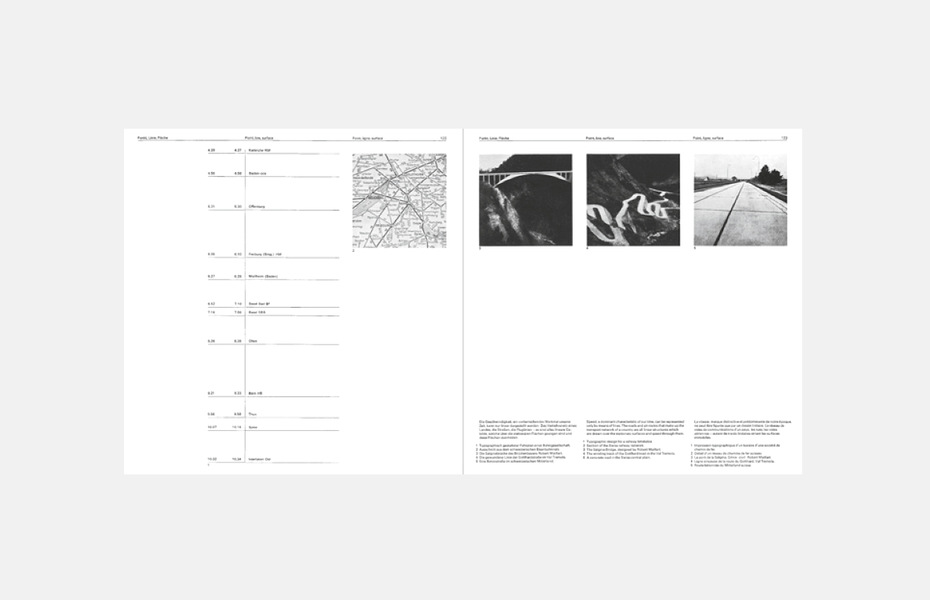
danke Emil Ruder
От ре­дак­ции Ров­но пять­де­сят лет на­зад в из­да­тель­стве Ар­ту­ра Ниг­гли (го­род Ни­дертёй­фен, Швей­ца­рия) вы­шла кни­га Эми­ля Ру­де­ра (1914–1970) «Ти­по­гра­фи­ка». В то вре­мя гра­фи­че­ский ди­зайн в Ев­ро­пе ис­пы­ты­вал не­обык­но­вен­ный подъ­ём, ко­то­рый во мно­гом был свя­зан с де­я­тель­но­стью учеб­ных цен­тров в Ба­зе­ле, Цю­ри­хе и Уль­ме. Пе­ре­до­вая шко­ла ди­зай­на, по­явив­ша­я­ся в не­драх Ба­у­ха­у­за, воз­ро­жда­лась в но­вом, по­сле­во­ен­ном кон­тек­сте. Вме­сте с про­мыш­лен­ным ди­зай­ном и ар­хи­тек­ту­рой но­вую жизнь по­лу­чи­ла и ти­по­гра­фи­ка на пра­вах уни­каль­ной дис­ци­пли­ны со сво­и­ми пе­да­го­ги­че­ски­ми ме­то­ди­ка­ми. Уси­ли­я­ми Эми­ля Ру­де­ра, Ад­ри­а­на Фру­ти­ге­ра, Мак­са Бил­ла, Ар­ми­на Хоф­ма­на и дру­гих ди­зай­не­ров она об­ре­ла то, что не мог дать ти­по­гра­фи­ке аван­гард 20-х: фун­да­мент, осно­ва­тель­ность, кон­цеп­ту­а­лизм. Квад­рат­ный том Ру­де­ра, из­дан­ный на трёх язы­ках (не­мец­ком, ан­глий­ском и фран­цуз­ском), пред­став­ля­ет со­бой уни­каль­ный кон­спект лек­ций, ко­то­рые ти­по­граф чи­тал в те­че­ние 20 лет в Ба­зель­ской выс­шей шко­ле ремё­сел. Труд Ру­де­ра бы­стро рас­про­стра­нил­ся в Ев­ро­пе и Аме­ри­ке и вы­дер­жал ряд пе­ре­из­да­ний как в Швей­ца­рии, так и в дру­гих стра­нах.
Вы­пу­щен­ный Дмит­ри­ем Аро­но­вым осе­нью ре­принт со­вет­ско­го из­да­ния «Ти­по­гра­фи­ки» (М.: Кни­га, 1982; пе­ре­вод с не­мец­ко­го, по­сле­сло­вие и ком­мен­та­рий Мак­си­ма Жу­ко­ва) — но­вый ру­беж в ис­то­рии этой кни­ги. За­но­во свёр­стан­ная и на­бран­ная из­да­те­лем, она при­бли­же­на ком­по­зи­ци­он­но и по­ли­гра­фи­че­ски к швей­цар­ско­му пер­во­из­да­нию. Не­смот­ря на то что в рус­ском из­да­нии нет па­рал­лель­ных тек­стов на дру­гих язы­ках (и, со­от­вет­ствен­но, трёх­ко­лон­ни­ка), в его осно­ве ле­жит мо­дуль­ная сет­ка Ру­де­ра, ко­то­рую не уда­лось в точ­но­сти со­хра­нить из-за по­греш­но­стей по­ли­гра­фии в 1982 го­ду в Моск­ве. В ны­неш­нем ре­прин­те и фор­мат, и вы­бор ма­те­ри­а­лов, и пе­чать не на­ру­ша­ют струк­ту­ру по­лей и про­пор­ции, из­бран­ные Ру­де­ром для сво­ей кни­ги.
По­че­му это важ­но — про­из­не­се­но в вы­ступ­ле­нии од­но­го из са­мых та­лантли­вых ти­по­гра­фов со­вре­мен­но­сти Гель­му­та Шми­да об Эми­ле Ру­де­ре в свя­зи со сто­ле­ти­ем со дня ро­жде­ния по­след­не­го. Один из вер­ных уче­ни­ков Ру­де­ра, Шмид рас­ска­зы­ва­ет об ис­то­рии воз­ро­жде­ния этой кни­ги в 2001 го­ду в из­да­тель­стве Niggli по­сле че­ре­ды гру­бых и пи­рат­ских пе­ре­из­да­ний «Ти­по­гра­фи­ки». В транс­крип­те ре­чи ска­за­но, ра­зу­ме­ет­ся, не толь­ко об этом. Бла­го­да­ря Шми­ду мы мо­жем по­гру­зить­ся в ат­мо­сфе­ру кур­са ти­по­гра­фи­ки в Выс­шей шко­ле ремё­сел в Ба­зе­ле. Имен­но ра­бо­ты уче­ни­ков Ру­де­ра тех лет со­ста­ви­ли осно­ву «Ти­по­гра­фи­ки» — кни­ги не про то, как де­лать, не про кро­хо­бор­ство в на­бо­ре и су­е­ту пра­вил и ис­клю­че­ний, а про мыш­ле­ние, шко­лу, уме­ние вы­стра­и­вать струк­ту­ру и мыс­лить ти­по­гра­фи­че­ски.
danke Emil Ruder
Речь об Эми­ле Ру­де­ре к 100-ле­тию
со дня ро­жде­ния. То­кио, 2014
Най­ти и со­хра­нить твор­че­ский сти­мул в ис­ход­ной за­да­че — са­мое важ­ное для Ру­де­ра. Его ме­тод обрёл вне­вре­мен­ное ка­че­ство, вот по­че­му он так зна­чим и при­вле­ка­те­лен се­го­дня...
Я сра­зу по­нял, что нуж­но смот­реть по сто­ро­нам: в Швей­ца­рии ти­по­гра­фи­ка од­на, в Ба­зе­ле — дру­гая, а ти­по­гра­фи­ка Эми­ля Ру­де­ра не ­по­хо­жа ни на од­ну из них. «Да­же не по­ка­зы­вай, я знаю, что они там де­ла­ют», — ска­зал Ру­дер, ко­гда я по­пы­тал­ся про­де­мон­стри­ро­вать ему свои ра­бо­ты. «Там» — это в За­пад­ной Гер­ма­нии, на гра­ни­це со швей­цар­ским Ба­зе­лем. Так слу­чи­лось, что я жил по ту сто­ро­ну гра­ни­цы, в го­ро­де Вайль-ам-Райн. Путь до Ба­зе­ля был лёг­кой про­гул­кой к гра­ни­це. Путь к ти­по­гра­фи­ке ле­жал че­рез гра­ни­цу. В ап­ре­ле 1960 го­да я по­лу­чил раз­ре­ше­ние на пе­ре­се­че­ние по­гра­нич­ной зо­ны, что­бы стать бли­же к ти­по­гра­фи­ке.
Мо­им пер­вым ти­по­граф­ским опы­том под ру­ко­вод­ством Эми­ля Ру­де­ра бы­ли два­дцать ва­ри­ан­тов не­боль­шой га­зет­ной ре­кла­мы. Во­семь из них вы­ста­ви­ли в но­я­бре 1961 го­да в Graphisches abc, не­мец­ком жур­на­ле для на­чи­на­ю­щих гра­фи­че­ских ди­зай­не­ров. Во вве­де­нии бы­ло на­пи­са­но: «Юный уче­ник с юго-вос­то­ка фе­де­ра­тив­ной рес­пуб­ли­ки и се­рия ре­клам­ных ма­те­ри­а­лов, из­го­тов­лен­ных им под ру­ко­вод­ством гос­по­ди­на Эми­ля Ру­де­ра». Жур­нал ис­поль­зо­вал мой ва­ри­ант об­лож­ки, ко­то­рый я со­здал под яв­ным вли­я­ни­ем Ру­де­ра и от­пра­вил под его же име­нем. «Нам за­пла­тят?» — мо­мен­таль­но от­ре­а­ги­ро­вал Ру­дер, ко­гда я по­ка­зал ему этот но­мер жур­на­ла.
Курс ти­по­гра­фи­ки в Выс­шей шко­ле ремё­сел в Ба­зе­ле
В 1950-х и 60-х го­дах Ба­зель стал цен­тром при­тя­же­ния для мо­ло­дых ти­по­гра­фов и ди­зай­не­ров из раз­ных стран во мно­гом бла­го­да­ря Ру­де­ру и его ра­бо­там. Он учил ди­зай­не­ров мыс­лить ши­ро­ко, вос­пи­ты­вал на­бор­щи­ков и пе­чат­ни­ков, зна­ко­мил гра­фи­че­ских ди­зай­не­ров с ти­по­гра­фи­ей, вёл курс по вы­со­кой пе­ча­ти, да­вал ве­чер­ние уро­ки под эги­дой ба­зель­ско­го Со­ю­за ти­по­гра­фов (Handsetzer-Vereinigung Basel). Кро­ме то­го, Ру­дер раз­ра­бо­тал про­грам­му го­до­во­го кур­са ти­по­гра­фи­ки, на ко­то­рый еже­год­но при­ни­мал двух-трёх сту­ден­тов.
«Дорога в Базель» — опуб­ли­ко­ван­ный в 1997 го­ду из­да­тель­ством Robundo в То­кио сбор­ник очер­ков о ти­по­гра­фи­ке, на­пи­сан­ных уче­ни­ка­ми Эми­ля Ру­де­ра, даёт жи­вое пред­став­ле­ние об этих уро­ках. Мар­сель Не­бель, Рой Ко­ул, Гар­ри Бол­лер и Ганс-Ру­дольф Лу­тц, пи­шут о жиз­ни в Ба­зе­ле, по­ка­зы­ва­ют свои ра­бо­ты и де­мон­стри­ру­ют ис­точ­ни­ки вдох­но­ве­ния тех лет. В по­свящён­ном Ру­де­ру но­ме­ре жур­на­ла Idea Ки­о­но­ри Му­ро­га пи­шет: «„До­ро­га на Ба­зель“ Гель­му­та Шми­да — это сбор­ник сви­де­тельств тех, ко­му по­счаст­ли­ви­лось со­при­кос­нуть­ся с ге­ни­ем Эми­ля Ру­де­ра. Ав­то­ры с бла­го­дар­но­стью вспо­ми­на­ют дни, про­ведён­ные с че­ло­ве­ком, ко­то­ро­го они лю­би­ли и ува­жа­ли».
Ганс-Ру­дольф Лу­тц учил­ся на год рань­ше ме­ня. Он стал увлечён­ным из­да­те­лем книг о ти­по­гра­фи­ке и со­ци­аль­ных про­бле­мах. Мы ча­сто об­ме­ни­ва­лись ра­бо­та­ми и иде­я­ми и со­би­ра­лись учре­дить пре­мию име­ни Эми­ля Ру­де­ра. Но од­на­жды я по­лу­чил пись­мо с мя­той за­пис­кой, на ко­то­рой зна­чи­лась да­та — 19 ян­ва­ря 1998 го­да.
«До­ро­гой Гель­мут, к со­жа­ле­нию, я вы­ну­жден по­ки­нуть этот мир... ни­че­го не по­де­ла­ешь... Хо­ро­шо, что я ещё мо­гу пе­ре­дать те­бе то рас­пи­са­ние, ко­то­рое Эмиль Ру­дер на­бро­сал при мне. Увы, к не­му при­ло­жил ру­ку и я. Где оно мо­жет со­хра­нить­ся луч­ше, как не в Оса­ке? Пе­ре­дай го­ря­чий при­вет Су­ми и Ни­коль. Ганс-Ру­ди Лу­тц».
«С Эми­ля Ру­де­ра на­ча­лось на­ше ти­по­гра­фи­че­ское пу­те­ше­ствие, с по­мо­щью Эми­ля Ру­де­ра мы ста­ли друж­ны, бла­го­да­ря Эми­лю Ру­де­ру ти­по­гра­фи­ка ста­ла од­ной из на­ших бес­ко­неч­ных тем».